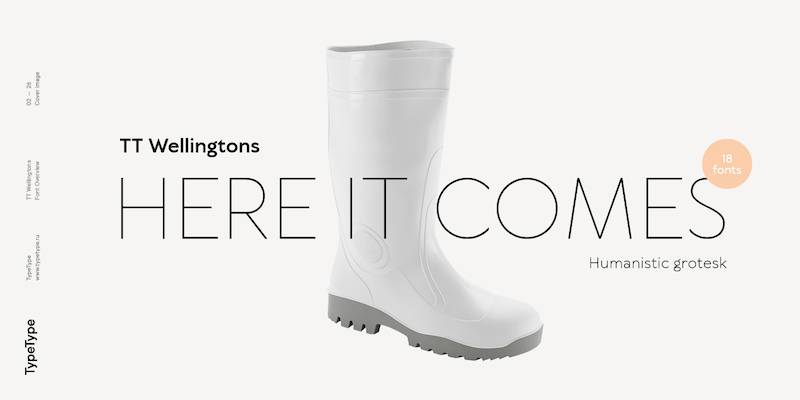
In einer Welt, in der digitales Immobilienvermögen König ist, sind die besten Schriftarten für Apps nicht nur ein Detail – sie sind der Herzschlag der Benutzerbindung.
Stellen Sie sich das vor: Sie haben den Code gemeistert, Ihre Funktionalität ist nahtlos, aber etwas fehlt. Es ist der stille Botschafter Ihrer Marke – die Typografie.
Auf den pixelperfekten Avenuen des App-Designs flüstert jede Kurve und Linie Ihrer gewählten Schriftart Ihren Benutzern zu.
Ich verstehe es.
Bei der Vielzahl von Schriftarten, die uns zur Verfügung stehen, wie wählen wir das Kronjuwel für unsere Apps aus? Einfach ausgedrückt, es ist eine Mischung aus Lesbarkeit, ästhetischer Harmonie und einer unheimlichen Fähigkeit, die Persönlichkeit Ihrer App widerzuspiegeln.
Am Ende dieses Textes werden Sie nicht nur die Kunst der Typografie im mobilen Design verstehen, sondern auch mit dem Wissen ausgestattet sein, um die Champions der Schriftartenwelt auszuwählen.
Tauchen Sie ein in:
- Die Enthüllung robuster Typografie-Richtlinien.
- Erkundung der Benutzeroberfläche-Wunder.
- Weisheit hinter Schriftarten-Paarungen.
App-Schnittstellen verwandeln sich — lassen Sie Ihre mit einwandfreier Typografie widerhallen.
Die besten Schriftarten für Apps
| Schriftart | Stil | Lesbarkeit | Unterscheidbarkeit | Verfügbarkeit |
|---|---|---|---|---|
| Roboto | Sans-serif | Hoch | Moderat | Kostenlos (Google Fonts) |
| Open Sans | Sans-serif | Hoch | Moderat | Kostenlos (Google Fonts) |
| Arial | Sans-serif | Sehr hoch | Niedrig (häufig) | Weit verbreitet |
| Montserrat | Sans-serif | Moderat | Hoch | Kostenlos (Google Fonts) |
| Nunito Sans | Sans-serif | Hoch | Moderat | Kostenlos (Google Fonts) |
| Poppins | Sans-serif | Hoch | Hoch | Kostenlos (Google Fonts) |
| Lato | Sans-serif | Hoch | Moderat | Kostenlos (Google Fonts) |
| Avenir | Sans-serif | Hoch | Hoch | Kostenpflichtig |
| Manrope | Sans-serif | Hoch | Moderat | Kostenlos (Google Fonts) |
| TT Wellingtons | Sans-serif | Moderat | Markant | Kostenpflichtig |
| Clash Grotesk | Sans-serif | Moderat | Markant | Kostenpflichtig |
| Nexa | Sans-serif | Hoch | Markant | Kostenpflichtig |
| Gilroy | Sans-serif | Hoch | Hoch | Kostenpflichtig |
| Proxima Nova | Sans-serif | Hoch | Hoch | Kostenpflichtig |
| Lexend | Sans-serif | Hoch | Moderat | Kostenlos (Google Fonts) |
| Playfair Display | Serif | Moderat | Hoch | Kostenlos (Google Fonts) |
| Ageo | Sans-serif | Hoch | Markant | Kostenpflichtig |
| Brandon Grotesque | Sans-serif | Hoch | Hoch | Kostenpflichtig |
| Helvetica Now | Sans-serif | Sehr hoch | Moderat | Kostenpflichtig |
| SangBleu | Serif | Moderat | Hoch | Kostenpflichtig |
| Inter | Sans-serif | Hoch | Moderat | Kostenlos (Google Fonts) |
| Switzer | Sans-serif | Hoch | Moderat | Kostenpflichtig |
| Work Sans | Sans-serif | Hoch | Moderat | Kostenlos (Google Fonts) |
| DM Sans | Sans-serif | Hoch | Moderat | Kostenlos (Google Fonts) |
| SF Pro Display | Sans-serif | Sehr hoch | Moderat | Apple Produkte |
Beliebte Sans-Serif Schriftarten
Sans-serif Schriftarten – Sie sind die coolen, minimalistischen Trendsetter in der Welt der Schriftarten. Warum? Sie sind klar, sauber und oh-so-lesbar. Perfekt für diesen schlichten, modernen Look.
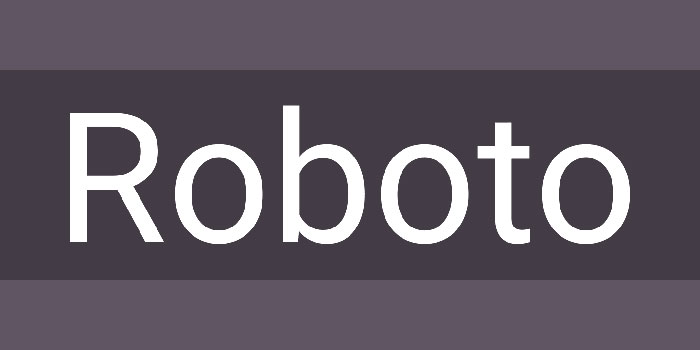
Stellen Sie sich vor, Sie betreten ein modernes, minimalistisches Café. Das ist Roboto. Es ist geometrisch, aber freundlich, ein Chamäleon für jedes App-Design.
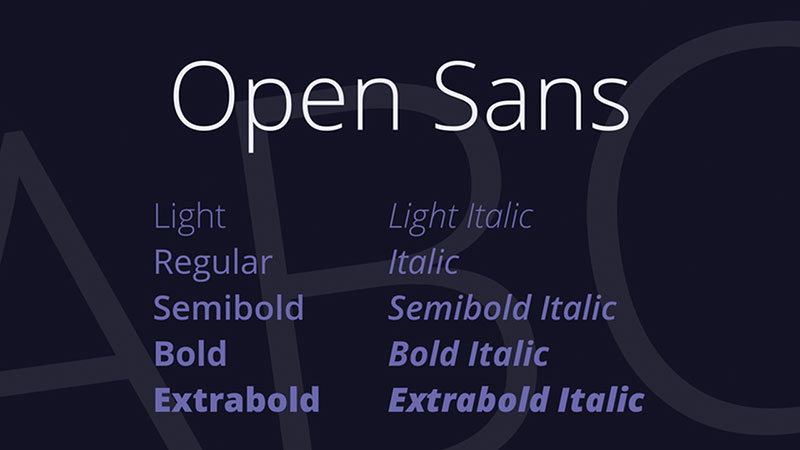
Es ist wie Ihr zugänglicher, freundlicher Nachbar. Humanistische Vibes machen es super lesbar, perfekt für Text und Überschriften.
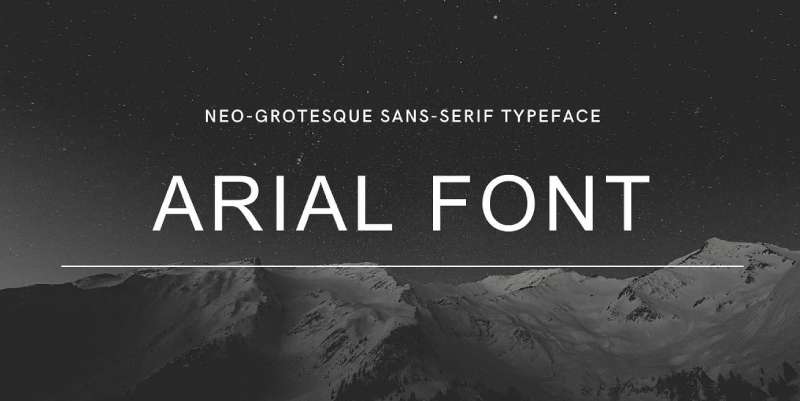
Alt, aber Gold. Arial ist wie dieser klassische Film, den man immer wieder sehen kann. Es ist überall, vom Telefon Ihrer Mutter bis zum Werbeplakat die Straße hinunter.
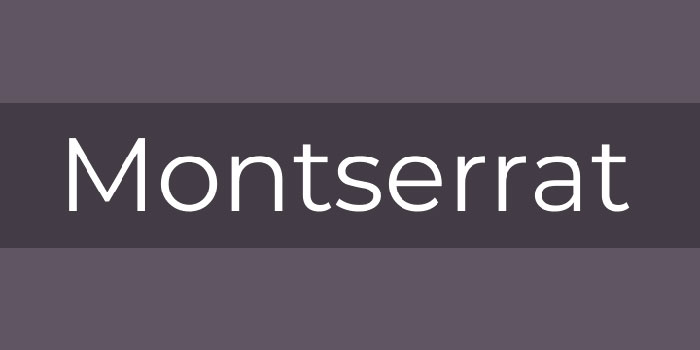
Haben Sie schon einmal diese trendigen, künstlerischen Poster gesehen? Montserrat könnte dabei gewesen sein. Es ist eine stilvolle Mischung aus geometrischen Linien und humanistischen Berührungen.
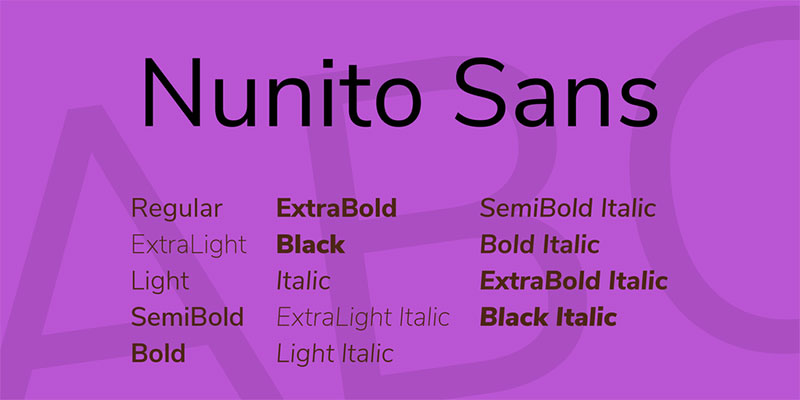
Stellen Sie sich ein Kissen vor – weich und bequem. Das ist Nunito Sans. Es ist entspannt, mit einem Hauch von Rundheit, ideal für informelle und freundliche Apps.
Moderne und geometrische Schriftarten
Wir biegen nun in die moderne Kunstgalerie der Schriftarten ein, geometrische Schriftarten sind die abstrakten Gemälde der Typografie. Sie drehen sich alles um klare Linien und Formen.
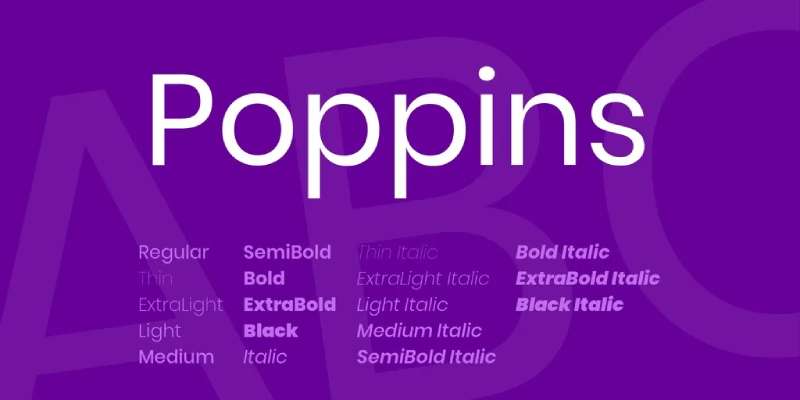
Poppins ist wie dieser Pop-Song, der fröhlich ist und Ihnen im Kopf bleibt. Es ist lebendig, mit einem geometrischen Herzschlag, perfekt für spaßige und dynamische Apps.
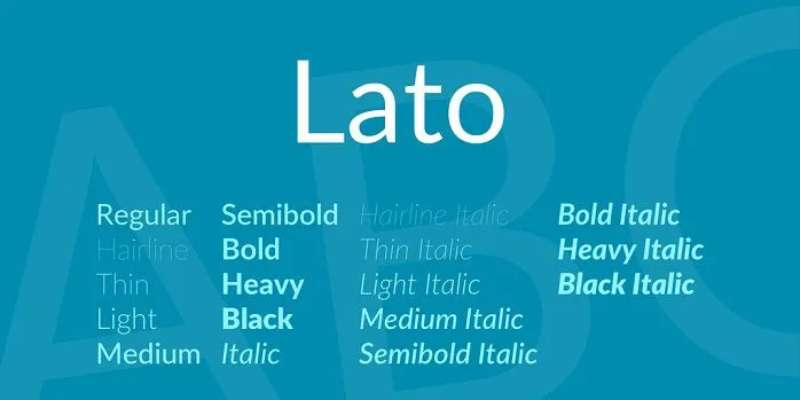
Stellen Sie sich einen sonnigen Sommertag vor. Lato ist hell, warm und einladend. Es ist großartig für Apps, die ein Gefühl von Komfort und Zugänglichkeit vermitteln möchten.
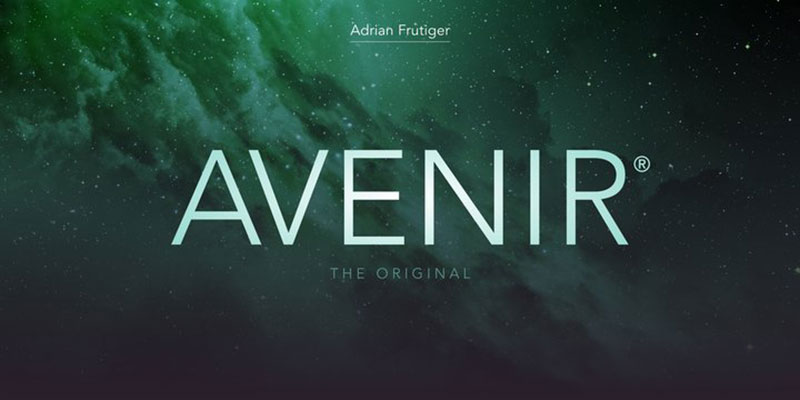
Wenn Schriftarten Autos wären, wäre Avenir Ihr schlanker, futuristischer Tesla. Es hat eine zukunftsorientierte Aura und bleibt dabei super lesbar.